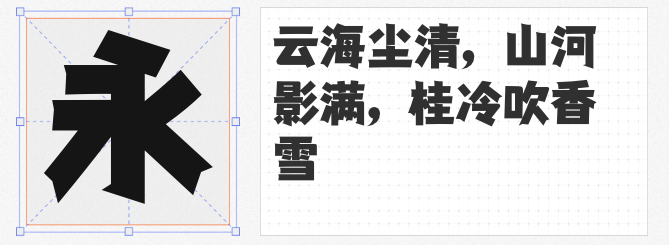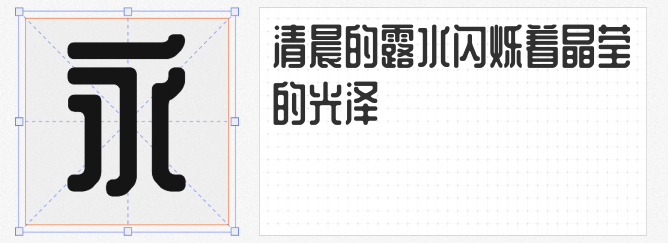
在设计领域,标题字体是吸引眼球、传递信息的关键元素。今天,为大家推荐四款免费商用且适合设计标题的字体,它们各具特色,能为你的作品增添独特魅力。
仓耳非白 W05 是一款极具风格的家族字体。其粗细对比强烈,结构方整,笔形简洁利落。在设计中,通过加粗笔形强调“黑”,增加细线强调“白”,形成鲜明对比。字形转折处直角处理,撇捺以直线表现,点变为圆形,方圆结合,让整体结构既刚硬又不失柔和,适合用于需要突出视觉冲击力的标题设计。
仓耳与墨 W05 风格现代且富有创意,强调厚重与力量。它将篆刻的“刀意”融入笔形处理,模拟刀刻痕迹,同时在转折和“口”字结构上采用圆转角处理,使字体内方外圆。配套的英文和标点部分与中文设计特点一致,混排时风格统一,非常适合用于追求前卫、醒目风格的标题设计。
WD-XL 滑油字 SC 是在站酷庆科黄油体基础上进行繁体(正体)中文补字扩充,并补全标点符号和功能。它字型创新,线条圆润,将笔划直角处理成半径为 4pt 的圆角,遵循笔划简化但不省略、角度尽量垂直的原则,视觉中心高。这款字体适合用于繁体(正体)中文环境的标题设计,能为作品增添一份圆润与灵动。
Aa 厚底黑 选用窄长字形,更具现代感。字形加入弧度较大的曲线和特别厚的底,让字体充满活泼气息。如果你想要打造一个时尚、活泼的标题,Aa 厚底黑绝对是个不错的选择。
这四款免费商用字体,风格各异,无论是追求粗细对比、现代创意、圆润创新还是活泼现代,都能满足你的需求。在设计标题时,不妨尝试使用它们,为你的作品带来全新的视觉体验。